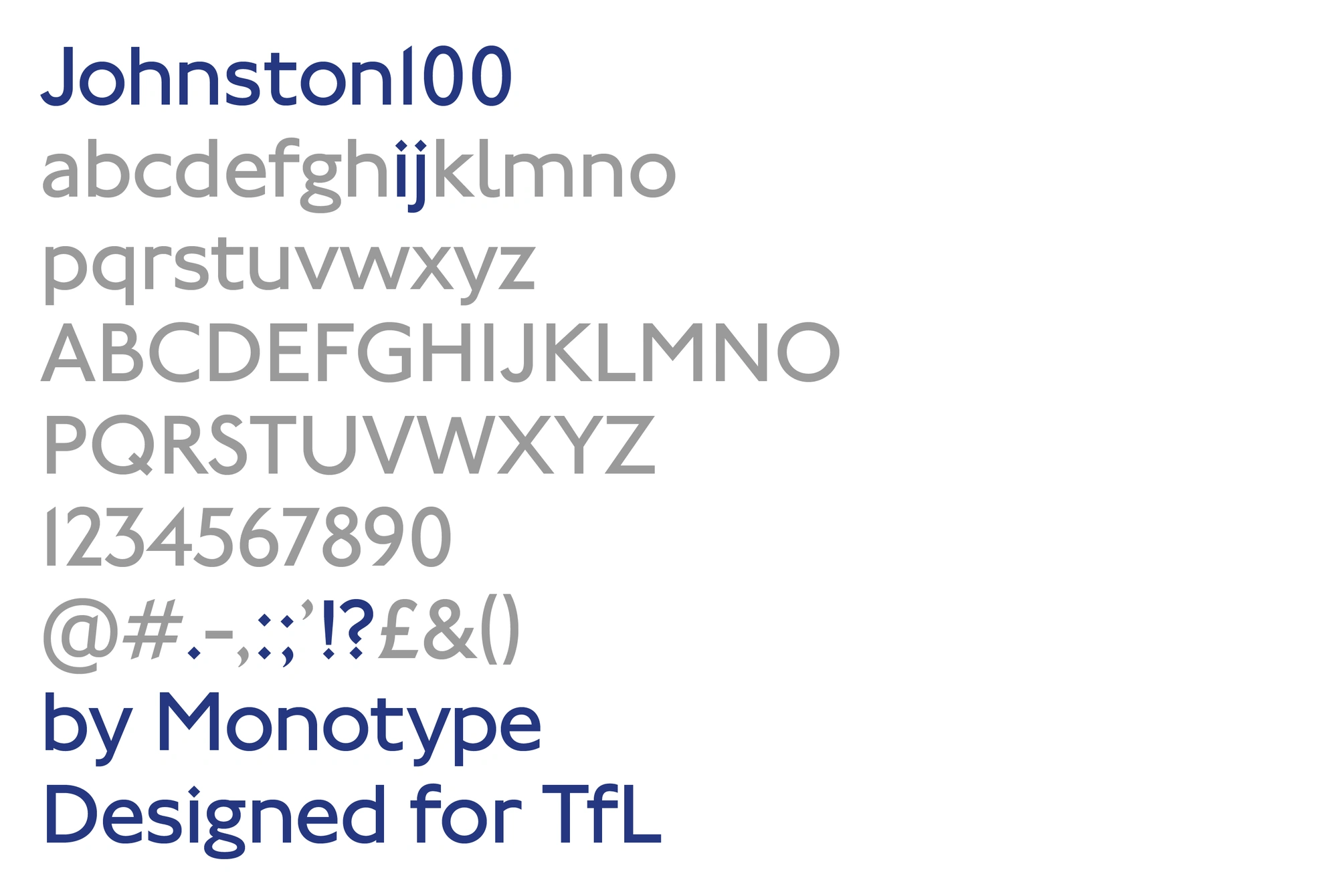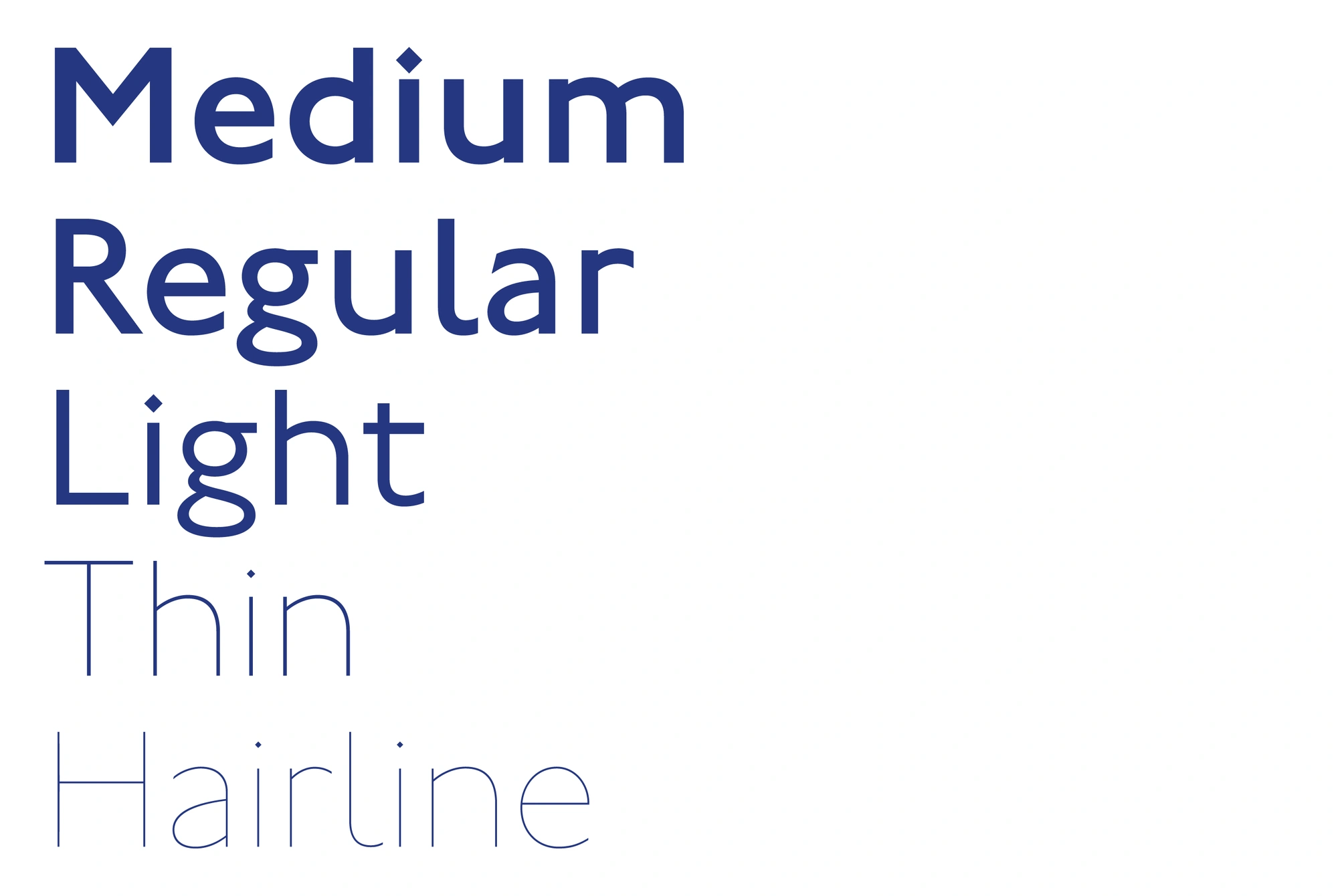
Londyńskie metro po 100 latach zmienia czcionkę, żeby... była czytelna na ekranach
Charakterystyczny napis „Underground” z pewnością kojarzy wiele osób, ale nie każdy wie, że stoi za nim czcionka Johnston, stworzona sto lat temu. Setne urodziny to idealny moment na odświeżenie fontu i przystosowanie go do nowych, cyfrowych czasów.
Londyńskie metro zmienia czcionkę, żeby... była czytelna na ekranach
Rzadko się nad tym zastanawiamy, ale w naszym życiu czcionki odgrywają ogromną rolę. Poza oczywistym wpływem na czytelność danego tekstu, czcionka stanowi też o jego charakterze, a co za tym idzie, atrakcyjności. Często wpływa też na szybkość, z jaką czytelnik jest w stanie czytać tekst. Unikatowy font może być ozdobą, a także wyróżnikiem wielu logotypów.
Na pierwszy rzut oka czcionki w przestrzeni publicznej kojarzą nam się z reklamami, ale gdyby się nad tym zastanowić, pełnią one ważną rolę w kwestiach komunikacji i bezpieczeństwa.
Krój Johnston stosowany w Londynie ma już 103 lata
Czcionka używana w londyńskim metrze nosi nazwę Johnston i została zaprojektowana w 1913 roku przez Edwarda Johnstona. Obecnie font jest wykorzystywany przez Transport for London (TfL) - jednostkę organizacyjną odpowiedzialną za całą komunikację publiczną, nie tylko tę podziemną.
103 lata po wprowadzeniu czcionki Johnston TfL postanowił ją unowocześnić. Okazuje się bowiem, że w dzisiejszych, cyfrowych czasach, Johnston nie radzi sobie tak dobrze, jak w druku.
Potrzebny był nowy font, który będzie czytelny na ekranach komputerów i smartfonów
W ten sposób powstał nowy krój Johnston100, który będzie dostępny w 5 grubościach, z czego dwie najcieńsze to zupełne nowości powstałe z myślą o ekranach. Johnston100 już teraz trafił na stronę internetową Transport for London. Nowy krój zaprojektował Monotype.
Co się zmieniło? Na pierwszy rzut oka bardzo niewiele, ale to raczej standard w tego typu odświeżeniach projektów. Zmieniły się grubości liter, odstępy między nimi, a także proporcje elementów w obrębie pojedynczych znaków. To kosmetyka, ale wszystkie te zmiany sprawią, że krój będzie czytelniejszy.
Nie jest to pierwszy przypadek zmiany kroju by dostosować go do cyfrowych realiów
Podobne zagrania możemy obserwować dość regularnie. Zmiana fontu być może nie zawsze ma taki kaliber jak ta w londyńskiej komunikacji miejskiej, ale co jakiś czas słyszymy o głośnych rebrandingach różnych marek.
Ostatnim głośnym przykładem jest nowe logo Facebooka, zmienione dokładnie w tym samym celu. Odświeżona wersja miała być po prostu czytelniejsza na ekranach smartfonów. Mało kto zauważy tę różnicę, ale z punktu widzenia marki jest to bardzo duża zmiana.
Stare logo Facebooka
Nowe logo Facebooka
Podobną transformację przeszło logo Google’a. Krój pisma zmienił się z szeryfowego na bezszeryfowy, czyli taki, którego końcówki znaków są proste i pozbawione ozdobników. Ten drugi typ jest standardem w Internecie i aż dziwne, że Google trzymało się szeryfów aż do 2015 roku.
Jeśli chodzi o logotypy, poprawa czytelności może dotyczyć nie tylko napisu, ale i sygnetu. W ostatnich latach dominuje tendencja spłaszczania logotypów, by były one jak najprostsze.